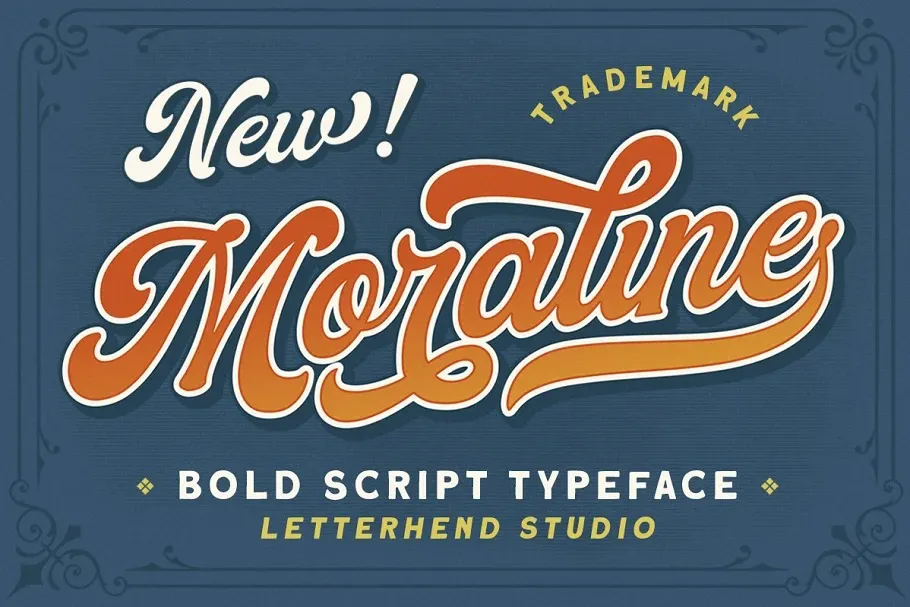
A Fonte ‘Moraline’ é uma escolha incrível para designers que buscam transpor um estilo elegante e sofisticado a seus trabalhos. Essa fonte script multifuncional oferece muitas alternativas diferentes para cada letra minúscula, permitindo uma grande variedade de aplicações. Este tipo especial de fonte foi projetada perfeitamente para ser usada em logotipos, headlines e sinalizações, além de outros formatos formais como cartões de convite, rótulos, selos, revistas, livros, cartas de cumprimento ou cartão de casamento, embalagens, moda, maquiagem, material de escritório, novela, etiquetas ou qualquer outra finalidade de propaganda. Com a ‘Moraline’, os designers podem criar um estilo único e memorável para seus projetos. Seja em sua empresa, seu site, ou em qualquer documento que você escreve, essa fonte oferece a precisão e o charme necessários para fazer uma impressão duradoura. Acreditamos que esta é uma excelente escolha para quem está procurando por uma fonte script elegante e versátil. Ela se destaca como uma opção ideal tanto para profissionais de design quanto para designers iniciantes em busca de uma solução perfeita para seus trabalhos.